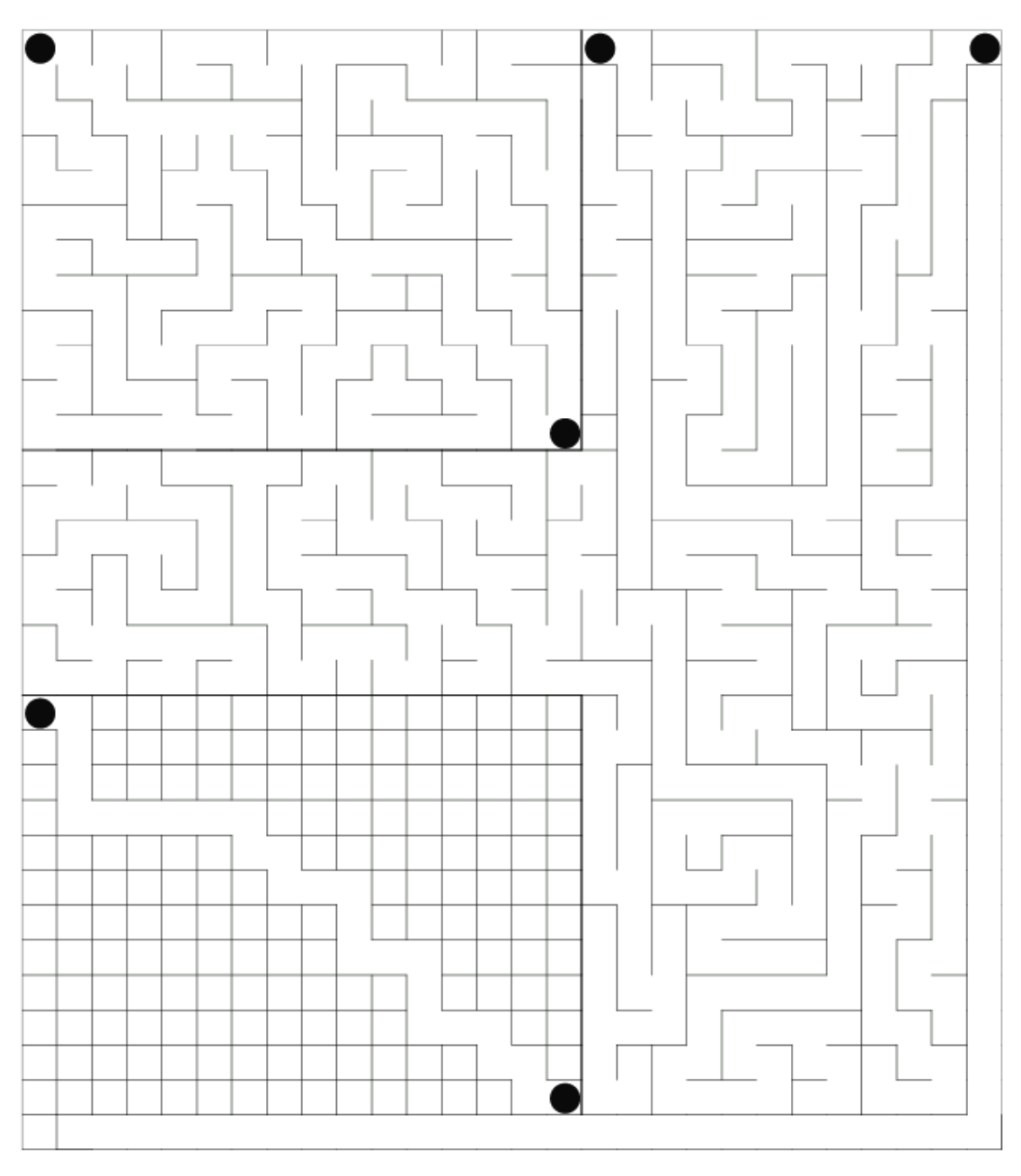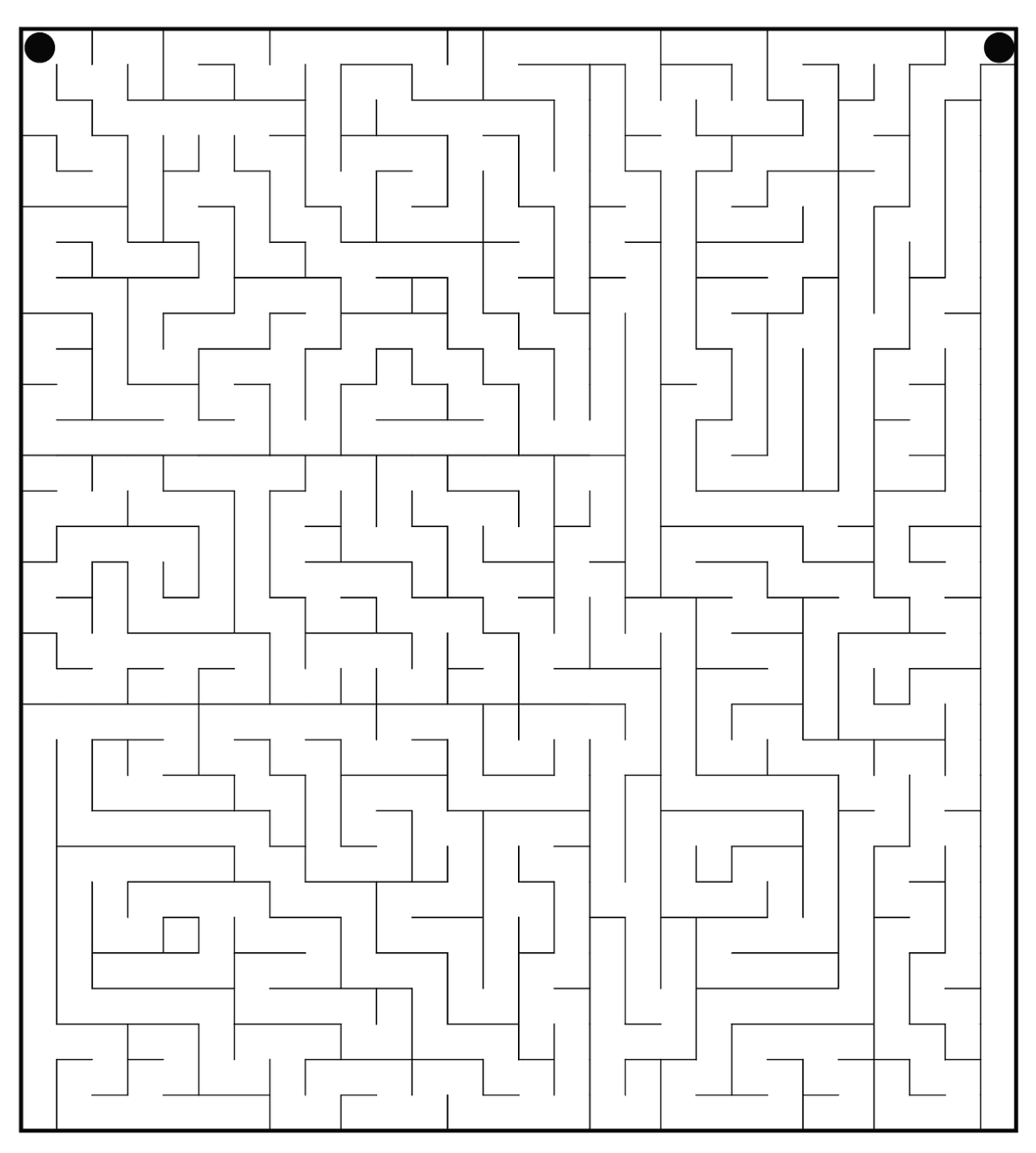
한글 미로찾기 폰트 작성중
미로를 지나간 길이 글자가 되는 미로를 만든지 오래됐다고 했는데 이미 30년 그 작업을 폰트에 적용해보기로 했습니다. (폰트 제작 초기부터 생각)
한글의 초성, 중성, 종성을 미로로 만들고 (벌수가 꽤 많음) 그걸 다시 조각내서 연결하는 방식으로 테스트해서 먼저 작성해봤습니다.
그러면 대충 이런식의 결과물이 나오는데... 제작에 대해서는 약간 다른 생각을 가지고 있어서 현재 이 버전은 프로토타입이라고 보면 됩니다. 왜냐면 직결식으로 만들면 안예쁘고 미로찾기가 재미없습니다. 맨날 똑같은 길을 지나가는 것이 목적이 아니고 새로운 길을 생성하는 방식을 찾으려고 하는 과정이기 때문입니다.
쥐도 아닌데 똑같은 길만 찾아다니면... 응?!?
하여간 길을 만들고 그 길의 패턴대로 최대한 글자를 채울수 있는 길을 만들 템플릿 제작이 우선이라서 그 다음은 조합하면 111,72자 만큼의 미로가 생성됩니다.
현재 사이즈별로 제작해야해서 18x32 로 하나 만들고 그 다음 비율별로 사이즈를 늘려갈 생각입니다. 사각형으로 만든 것도 다르게 표현할 예정입니다.
누더기를 깁어놓은 거 같은 모양이지만 테스트를 위한 것임을 보여드리기 위한 샘플입니다. 어디를 뚫고 연결하느냐에 따라 다른 미로찾기가 됩니다. 그러니까 배수관 같은 것을 틀고 닫고 하는 것에 따라 다른 미로찾기가 됩니다. 응?!?
1차 완성